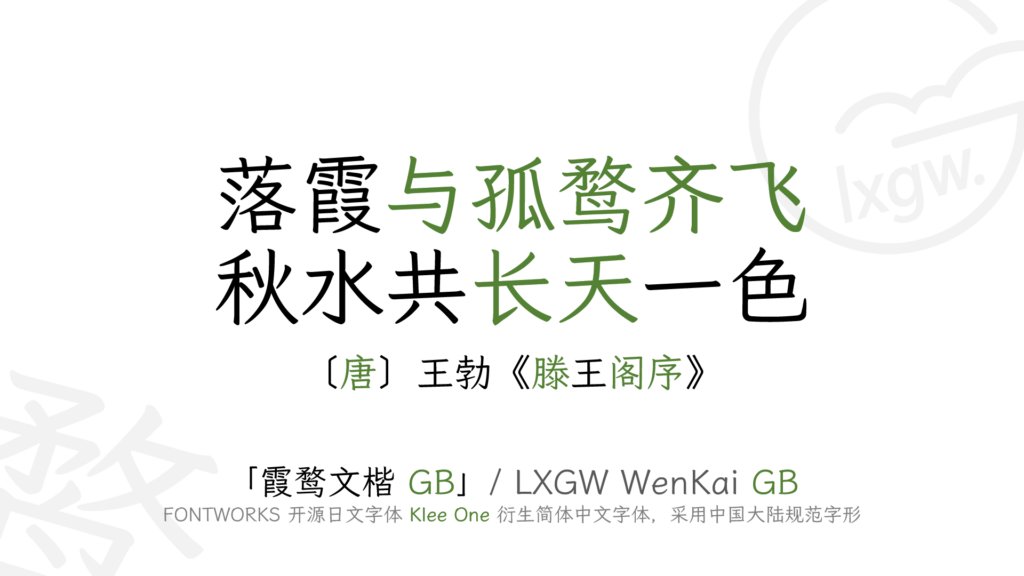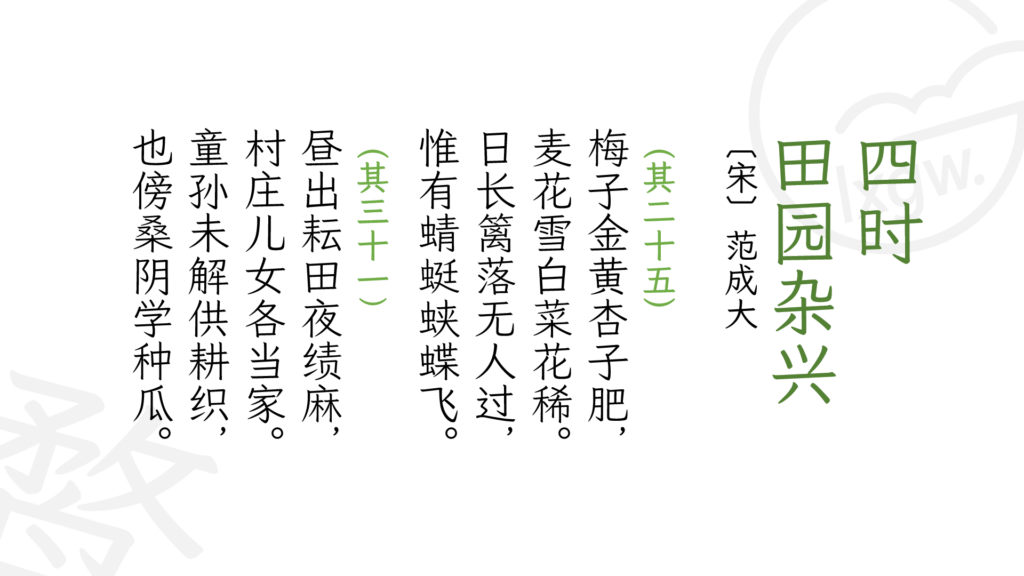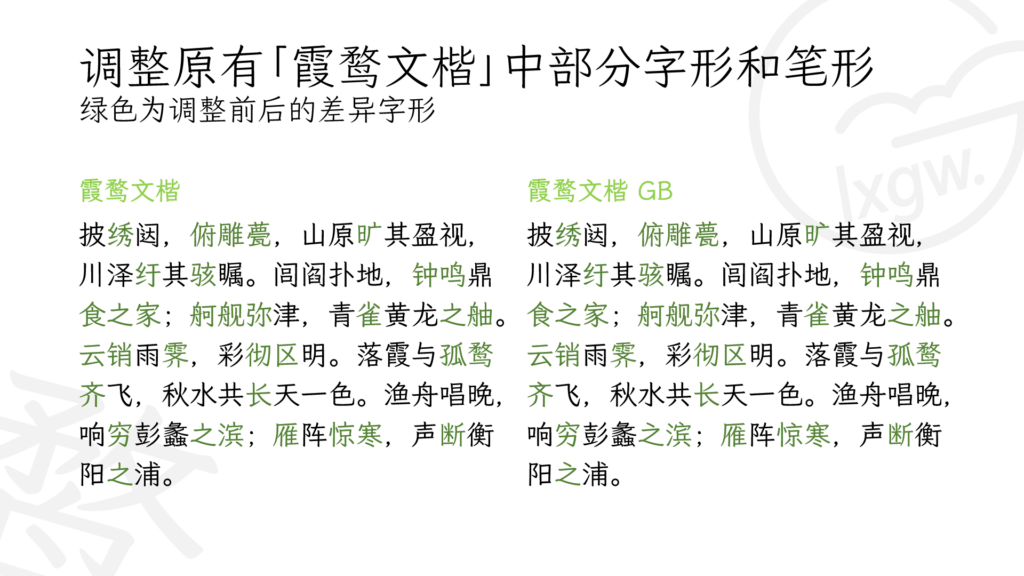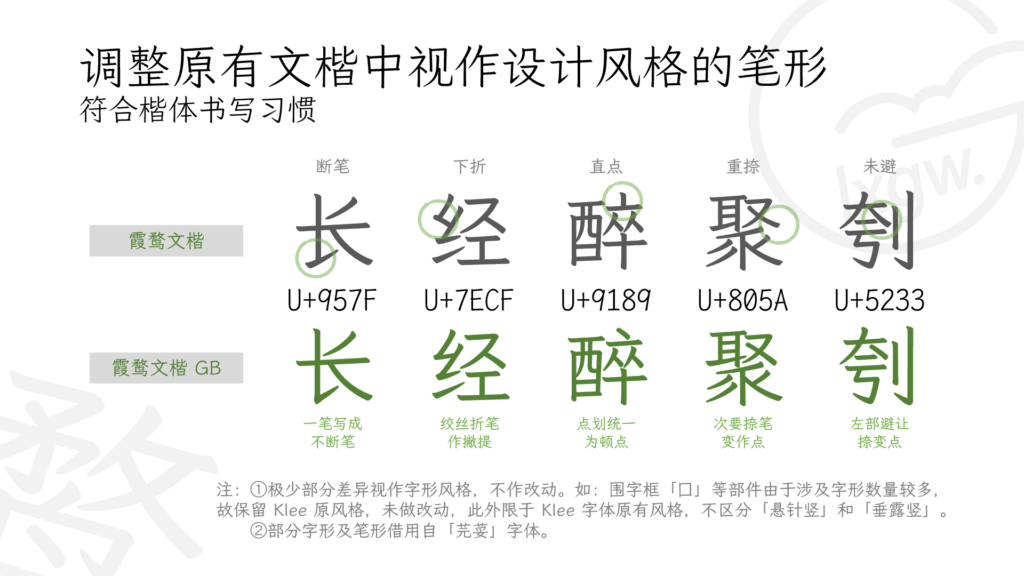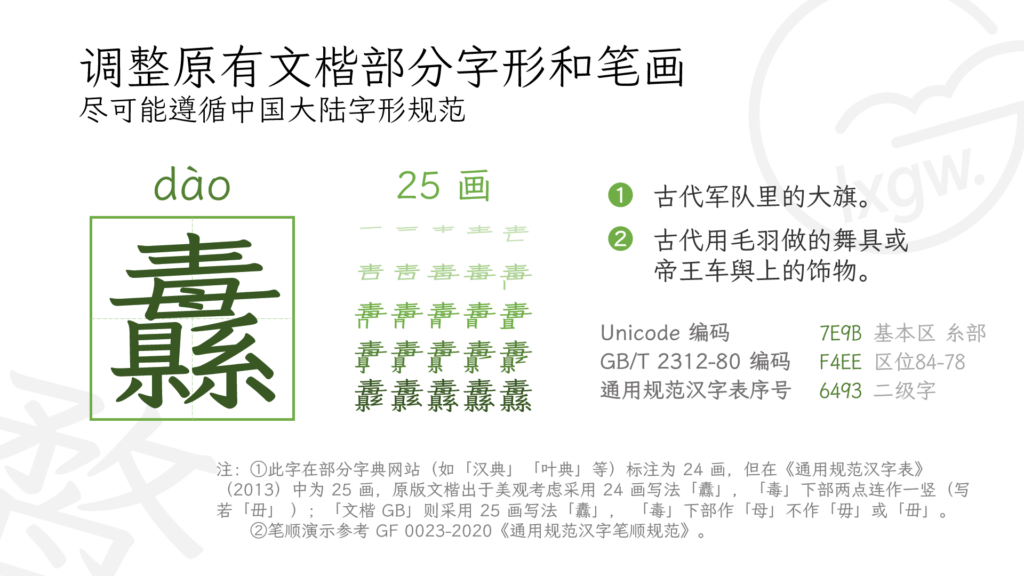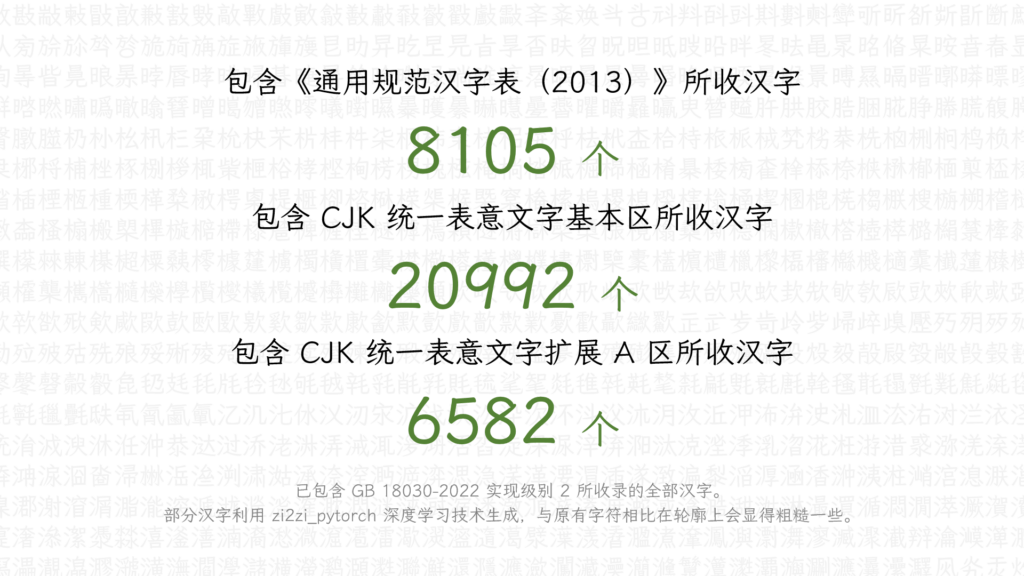
2020 年 12 月,日本著名字体厂商 FONTWORKS 在 GitHub 上释出了 7 款开源日文字体,其中 Klee One 字符数最多,兼有仿宋和楷体的特点,具有优雅的外观和温润的阅读感。与一般的教科书体相比,Klee One 保留了传统印刷字体的一些特征。2021 年,本人在其基础上增补和修改字形,制成「霞鹜文楷」/ LXGW WenKai 字体,受到广泛欢迎。
虽然「霞鹜文楷」修改了 GB/T 2312-1980 及《通用规范汉字表》范围内的汉字字形,使其接近中国大陆推行的新字形,但仍保留了 Klee One 印刷体的特征,如「亠」「宀」等起笔的直点,「㇙」「㇜」等笔画折角处断笔设计等,因此一些人认为「霞鹜文楷」的字形并不规范,不是「G 源字形」,不符合一般楷体的书写习惯。鉴于此,本人在「霞鹜文楷」的基础上,尽可能严格按照中国大陆的字形标准(G 源字形)对字形、笔形作进一步修改,继续沿用「霞鹜文楷」名称,增加「GB」后缀表示字形遵循国标。由于 Klee 字体的 Regular 字重太细,故选取原字体 SemiBold 字重作为本字体的 Regular 字重。
目前该字体包含《通用规范汉字表》(2013)所收录的 8105 个汉字、《现代汉语通用字表》(1988)所收录的 7000 个汉字,以及 GB/T 2312-1980 所收录的 6763 个汉字,并按需补充一些较常用的其他汉字(详见「外字初步整理一览表」),基本满足现代汉语(简体字)使用需要,并且适用于教育用途(如义务教育图书、少儿读物、字帖等)。自 v1.0 版本起,按照「繁异体及其他外字初步整理一览表」新增繁体字及 IICore 汉字支持。自 v1.320 版本起,补全完整的 CJK 统一汉字基本区和扩展 A 区,符合 GB 18030-2022 实现级别 2 的收字范围。